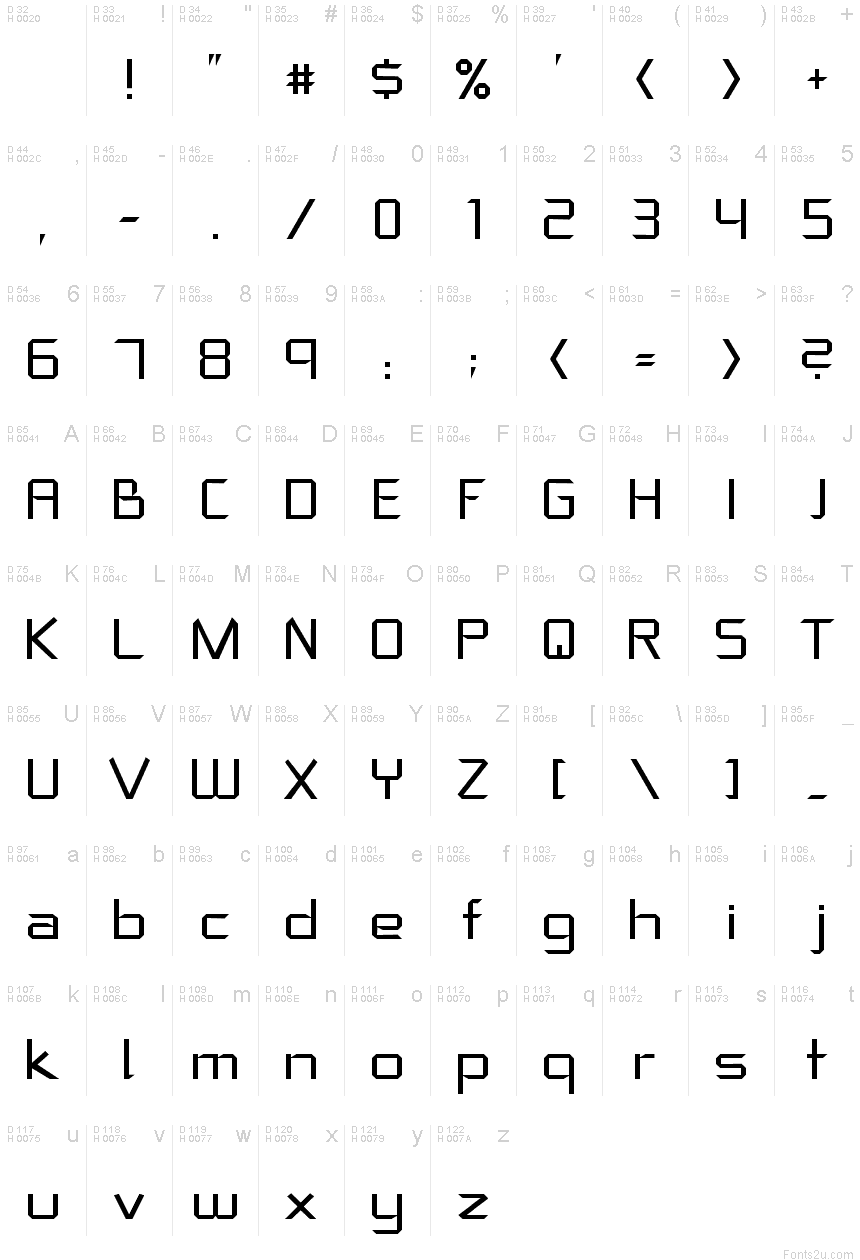
خط Crystal clear من Levi هو خط عرض (Display) تقني مجاني يتميز بتصميم نظيف مستوحى من لوحات الدوائر الإلكترونية. تمنح ضرباته المربعة وزواياه المقطوعة وإيقاعه العريض والمنخفض الكلمات طابعاً رقمياً أنيقاً، فهو حاد بما يكفي للعلامات التجارية المستقبلية، ومع ذلك فهو واضح وسهل القراءة.
استخدم Crystal clear لعناوين الألعاب، وشاشات تشغيل التطبيقات، ولافتات الرياضات الإلكترونية (eSports)، وملصقات Synthwave، وتغليف الأجهزة، وتراكبات البث، ومنشورات النوادي لإضفاء لمسة رقمية فورية. يعمل هذا الخط المجاني بشكل أفضل عند استخدامه بأحجام كبيرة، ويتماشى بشكل جميل مع خط "غروتيسك" (Grotesk) بسيط للنصوص الأساسية.